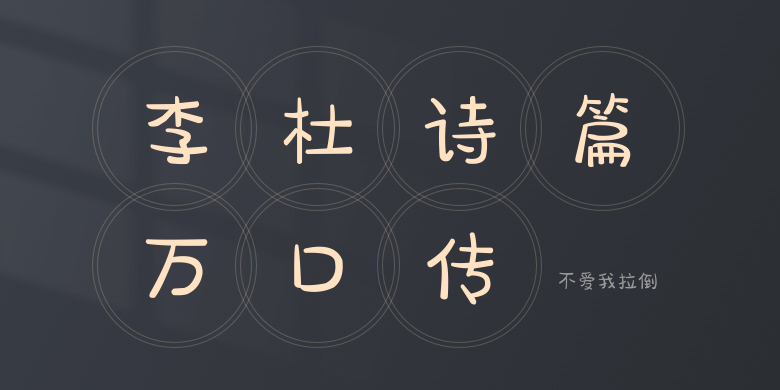
不爱我拉倒
不爱我拉倒,这款字体结构工整、笔画清晰,兼顾美观与易读性,适用于标题、正文、海报、包装、LOGO 等多种场景。字形优雅稳定,风格百搭耐看,适配日常排版与创意设计,让文字呈现更舒适、更具质感。不爱我拉倒一笔一画,皆是细节,以均衡的比例、流畅的线条打造舒适视觉体验,字形端正大气,风格简约现代。无论是商业设计、品牌宣传还是日常排版,都能轻松驾驭,让文字更有格调与力量。不爱我拉倒字体下载。